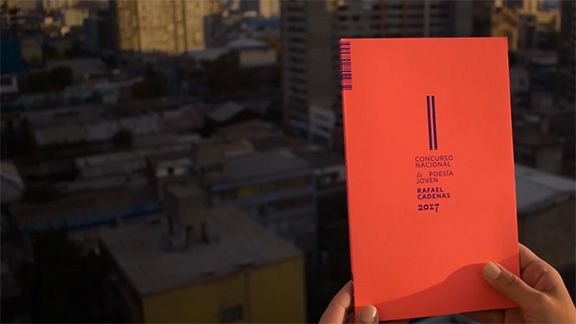
Los premios son valiosos si uno sabe tomar distancia y no creerse el cuento, a mi me generan una tensión que aprovecho para seguir exigiéndome a continuar haciendo las cosas bien.
El concurso »Los libros más bellos del mundo«, que se realiza en Leipzig, fue muy especial, pues hay una larga tradición de intercambio de Venezuela con Leipzig, una relación que ya suma 3 generaciones en 47 años y 25 diseñadores, sobre todo a través del trabajo de mi maestro Álvaro Sotillo quien ha recibido 3 Letras de Oro en ese concurso.
La otra cosa es que los premios ayudan a »validar« los caminos e investigaciones que uno se va planteando en el desarrollo del trabajo, a mi me impresionó mucho que el libro del II Concurso Nacional de Poesía Joven quedara seleccionado, es un libro que resume lo que hago: muy sencillo, sin solapas, pura tipografía, con el mínimo de recursos, casi a contrapelo de lo que normalmente se premia en esos concursos que es lo más experimental.
Por supuesto que verse al lado de diseñadores hiperfamosos —quizás demasiado— como Irma Boom, por ejemplo, es muy impresionante, y en ese sentido ayuda a dar a conocer el trabajo, no solo el mío, sino el de mi editorial y a lo mejor exagero el de una región, yo creo que los logros ya no son solo de Venezuela, también lo son de Chile, país donde resido y de donde es Javier Quintana, amigo tipógrafo que me permitió usar Violeta en el libro premiado, y de Colombia país donde mi editorial está también. Pero, si me preguntan de nuevo, creo que el premio más importante que he recibido es el II Premio Latinoamericano al Diseño Editorial, yo considero que ese esfuerzo de la Fundación El Libro es muy necesario para la región, para vernos un poco más, para pensarnos y por qué no: celebrarnos.